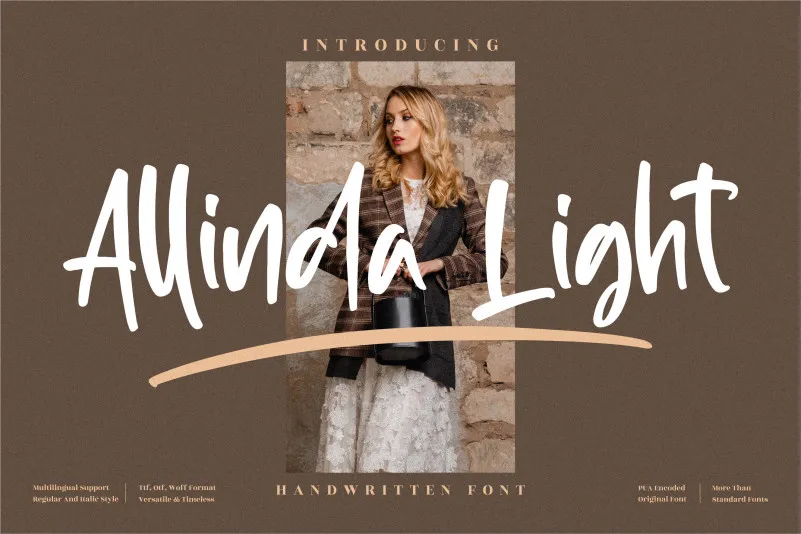
Aqui está uma versão breve e envolvente para a descrição do download da fonte Allinda Light na categoria Brush Fonts: Allinda Light é uma elegante tipografia escrita à mão, projetada com um toque refinado que transmite sofisticação e elegância. Perfeita tanto para projetos em fotografia quanto para aplicar em marcas de eventos especiais ou designs de luxo, esta fonte adquirem qualquer design com um toque autêntico e sofisticado. Seja você um designer gráfico que busca uma fonte única e contemporânea ou alguém em busca de uma opção elegante para usar em trabalhos de marca, Allinda Light será a escolha perfeita para criar um visual impecável. A fonte Allinda Light é ideal para aqueles que valorizam a arte escrita à mão no design gráfico. Sua aparência suave e única faz dela uma opção versátil tanto para projetos de fotografia quanto para marcas de eventos especiais ou qualquer outro tipo de trabalho em que um toque de sofisticação é desejado. A fonte Allinda Light atende perfeitamente os anseios de designers que desejam dar vida aos seus trabalhos com uma fonte que combina a elegância do escrita à mão com o modernismo da tipografia digital.